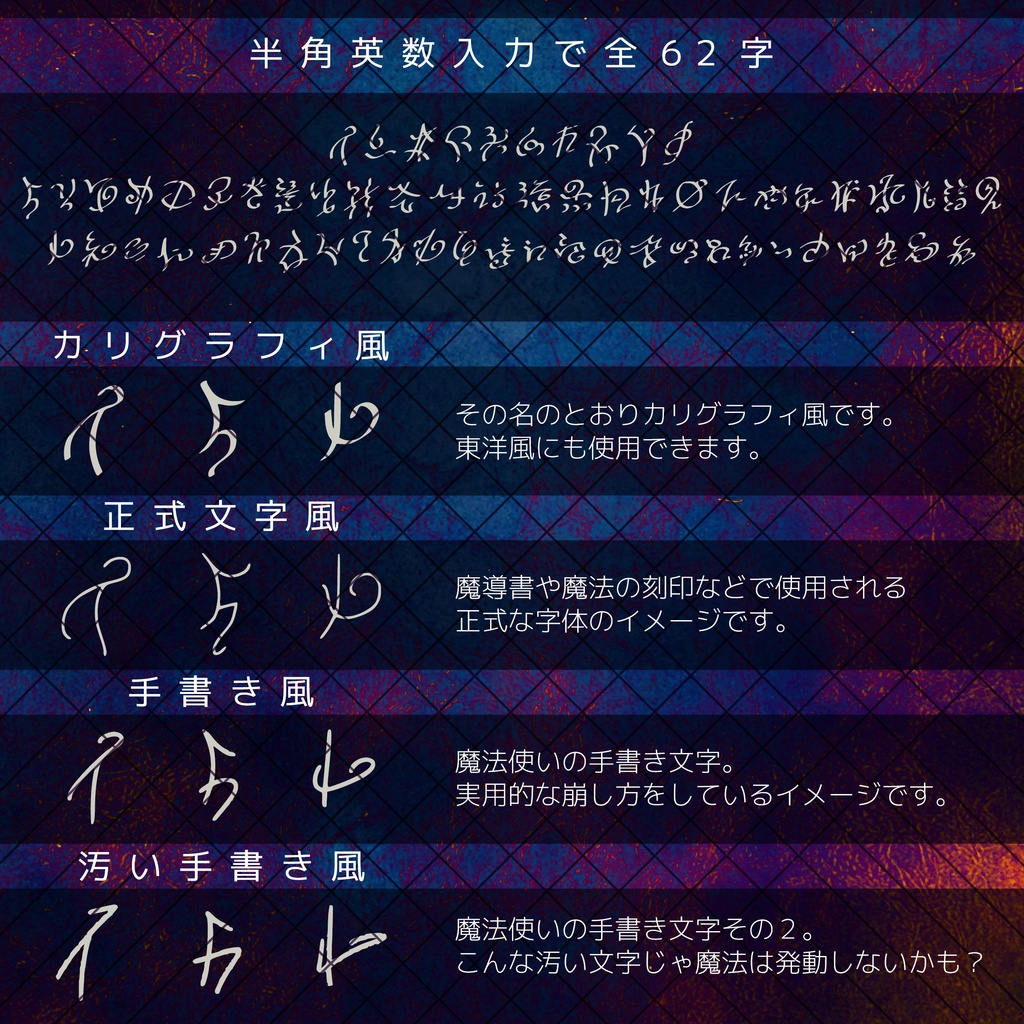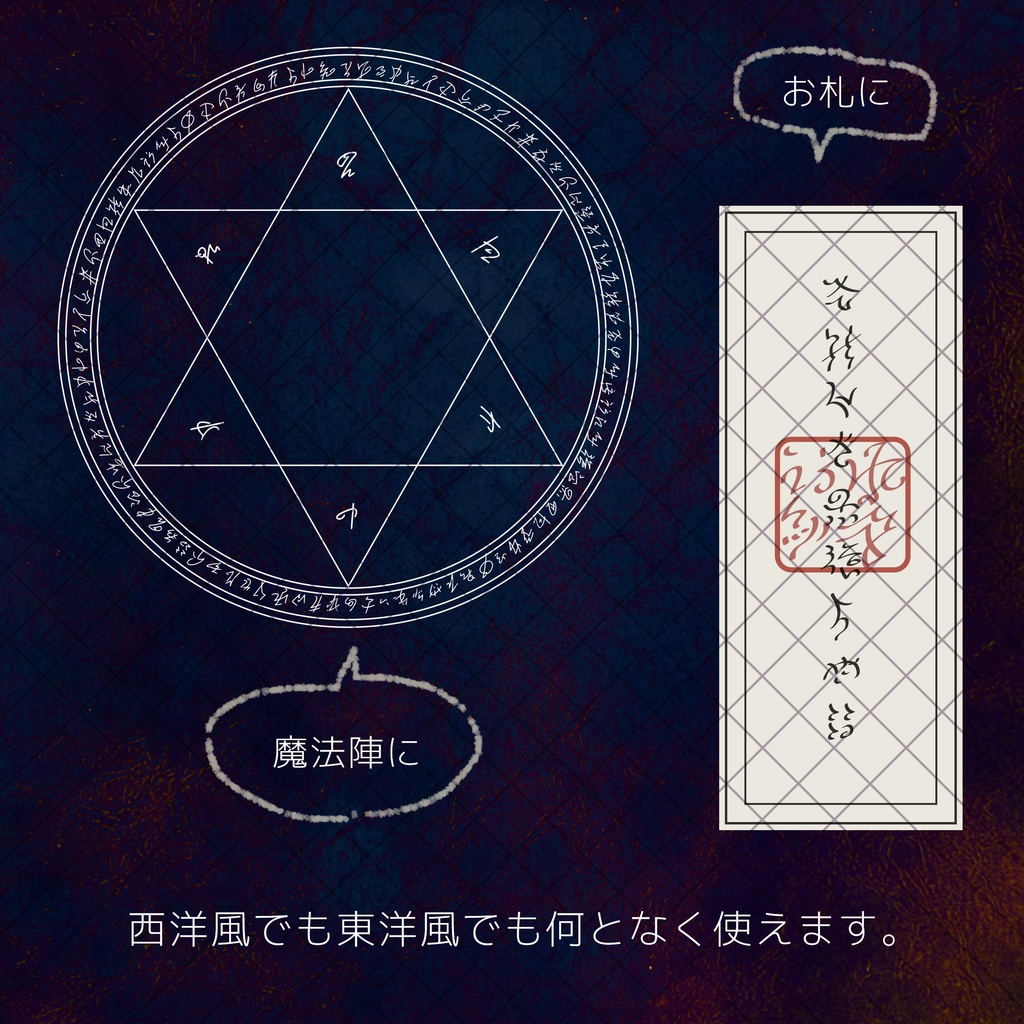
【無料お試し版有】フォント「魔女の魔法文字」
「魔女の使用する魔法文字」をイメージした架空の魔法文字フォントです。 素材集「魔女の手記帳」もよろしくお願いします! https://hireitcorp.booth.pm/items/4062905 ◎有料版は商用利用可(一部制限あり) ◎WEB、印刷、映像、ゲーム、ロゴマーク等、何にでも使用できます! ◎使用報告・クレジット表記不要(任意) ◎変形・加工可 ×自作発言、再配布、転売、誹謗中傷、反社会的行為、政治・宗教活動での使用は固く禁止しております。 ×当素材を使用したことによる全てのトラブルにおいては一切の責任を負いません。 詳しくは同梱の利用規約をご一読ください。 ※有料版購入前に必ず無料のお試し版で動作確認をしてください※